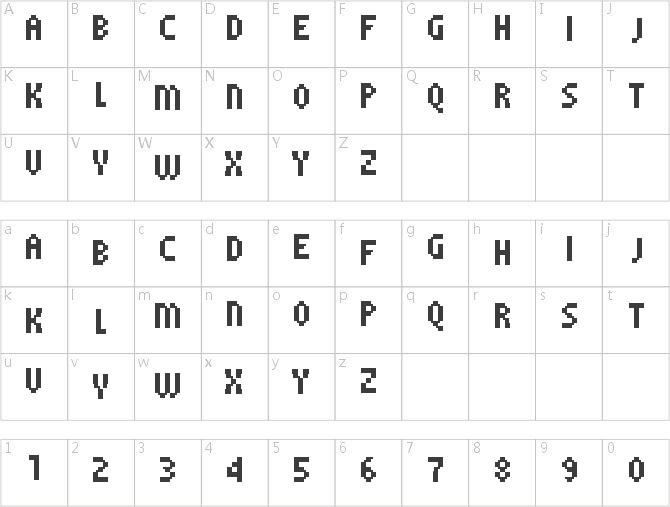
字体名称: pf_temp
pf_tempesta_five_compressed
pf_tempesta_five_compressed字体字库是一款让人赏心悦目、百看不厌的英文字体,适合各类广告和产品包装设计应用,字体大小0.06MB,格式为ttf字体,上传用户是Who am I?,作者/版权方为未知